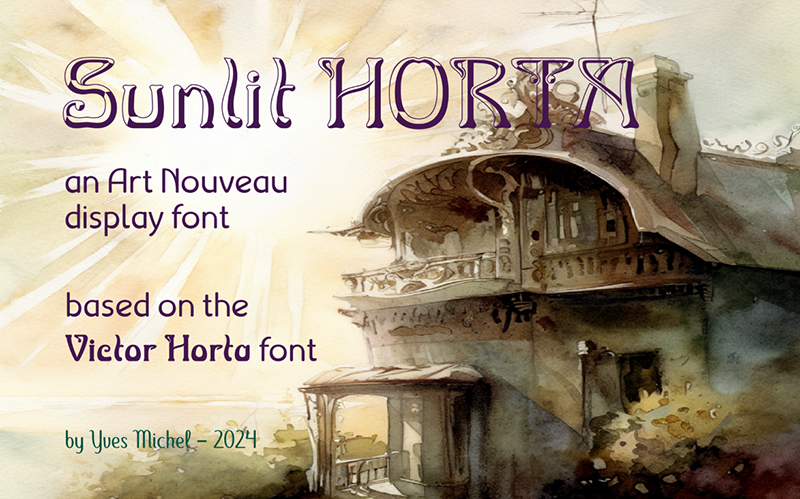
Font name: | Sunlit Horta |
Author: | Yves Michel |
Note by Yves Michel | |
La p�riode aux alentours de 1900 a produit les impressionnistes en peinture et l� Art Nouveau en architecture et graphisme. J�ai toujours admir� la police de caract�res Arnold Boecklin qui illustre remarquablement cette �poque. J�ai donc voulu cr�er une police dans cet esprit, sans tomber dans la copie ou l�imitation trop facile. Je l�ai nomm�e Victor Horta, en hommage � notre grand architecte belge, disciple d�Eug�ne Viollet-le Duc, pr�curseur de l�Art Nouveau. J'en ai tir� la pr�sente police emboss�e et �clair�e en haut � gauche _____________ The period around 1900 produced the Impressionists in painting and Art Nouveau in architecture and graphic design. I have always admired the Arnold Boecklin typeface, which is a remarkable illustration of this era. So I wanted to create a font in this spirit, without falling into copying or imitating it too easily. I named it Victor Horta, in tribute to our great Belgian architect, a disciple of Eug�ne Viollet-le-Duc, a precursor of Art Nouveau. The present derived font is embossed and lit from the left upper side. |